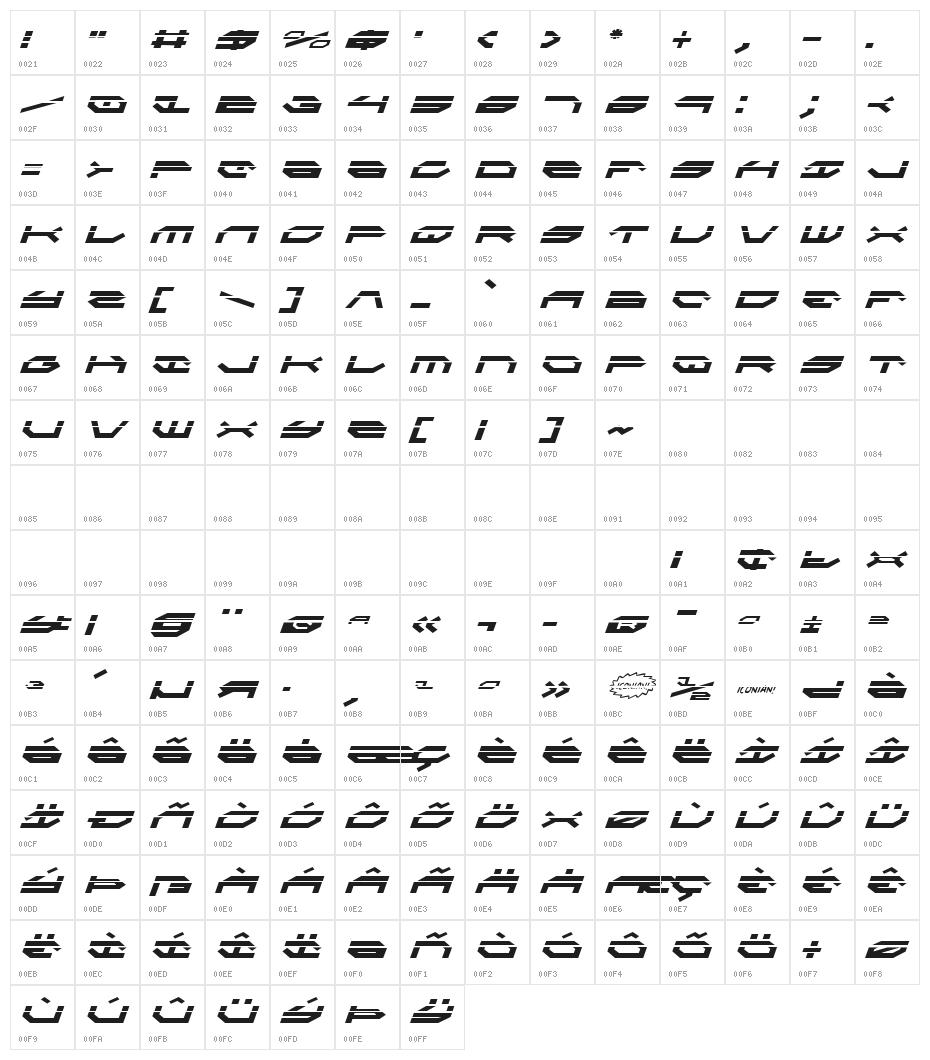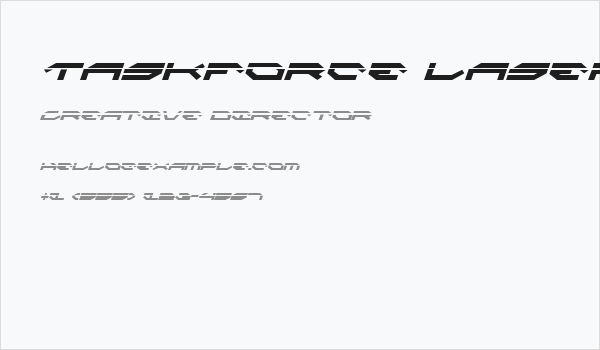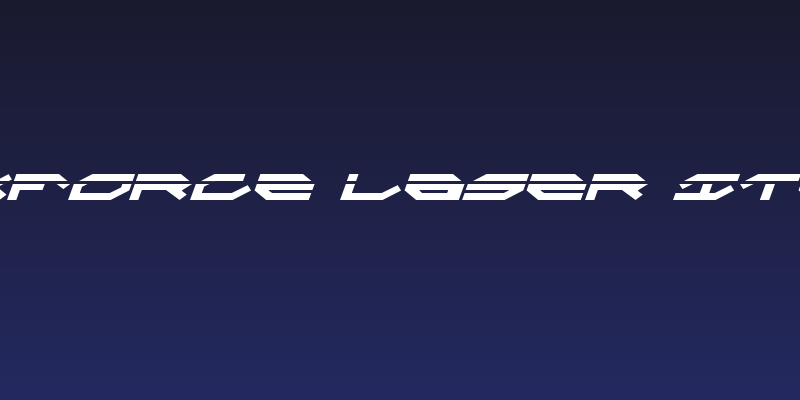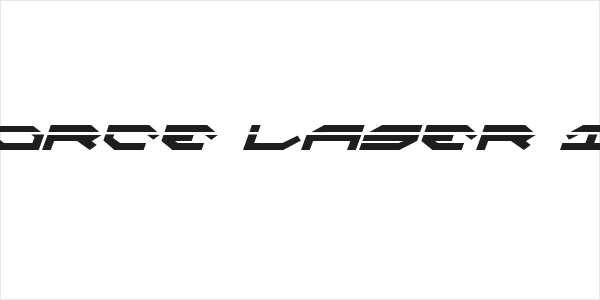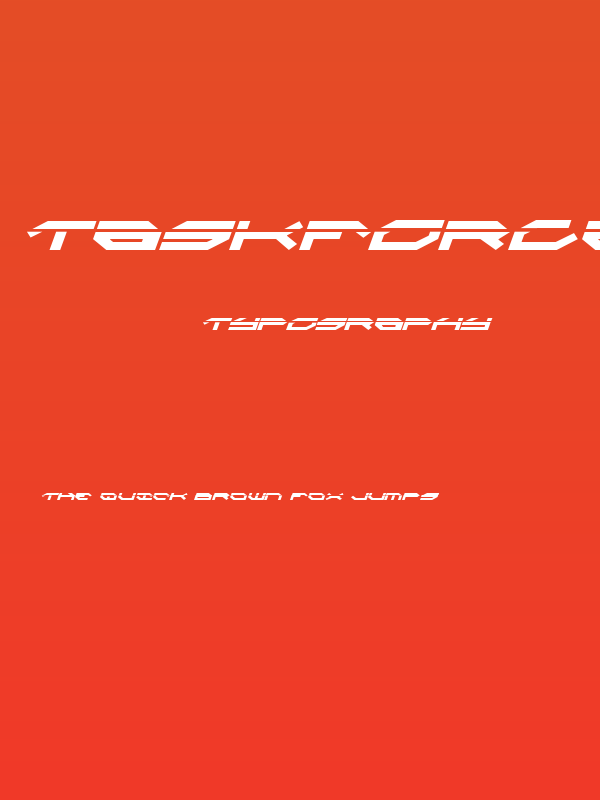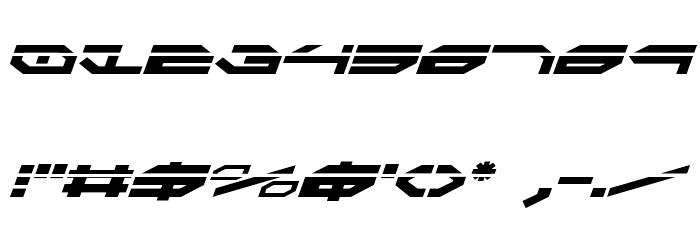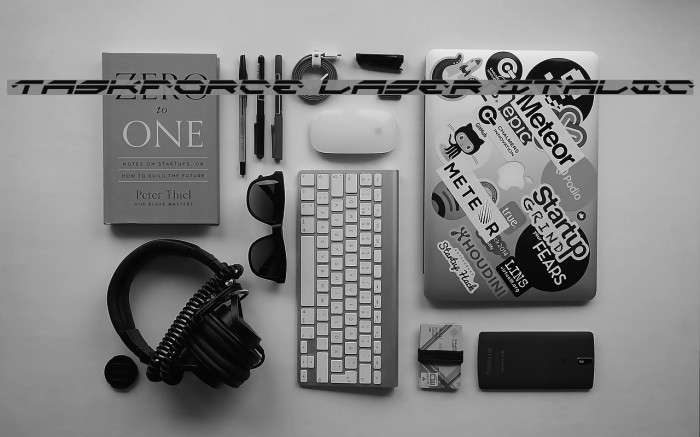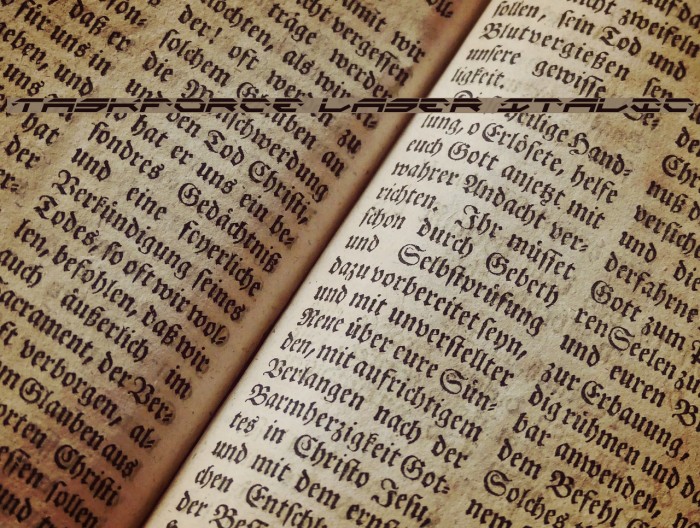
Taskforce Laser Italic Font
| 全体的なスタイル | Futuristic |
| おすすめプロジェクト | Ideal for sci-fi themed designs, video game titles, technology branding, and modern advertising. |